フォントかるた
2017年6月20日にフォントかるた制作チームが手掛けた絶対フォントファンに必見な「フォントかるた」のAmazonでの販売が開始された。
販売元は株式会社TART DESIGN OFFICEで、このかるたは、48枚の取り札にそれぞれの書体が使用されており、詠み上げられたフォント名の札を取るという絶対フォント感が試されるゲームになっている。
かるたには「愛のあるユニークで豊かな書体」と記載されている。
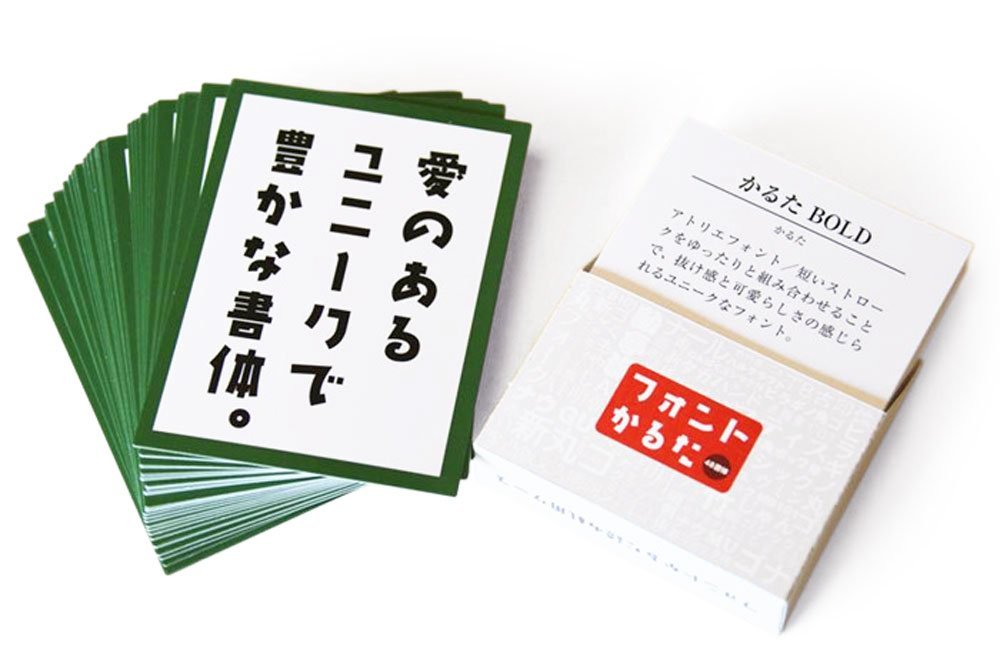
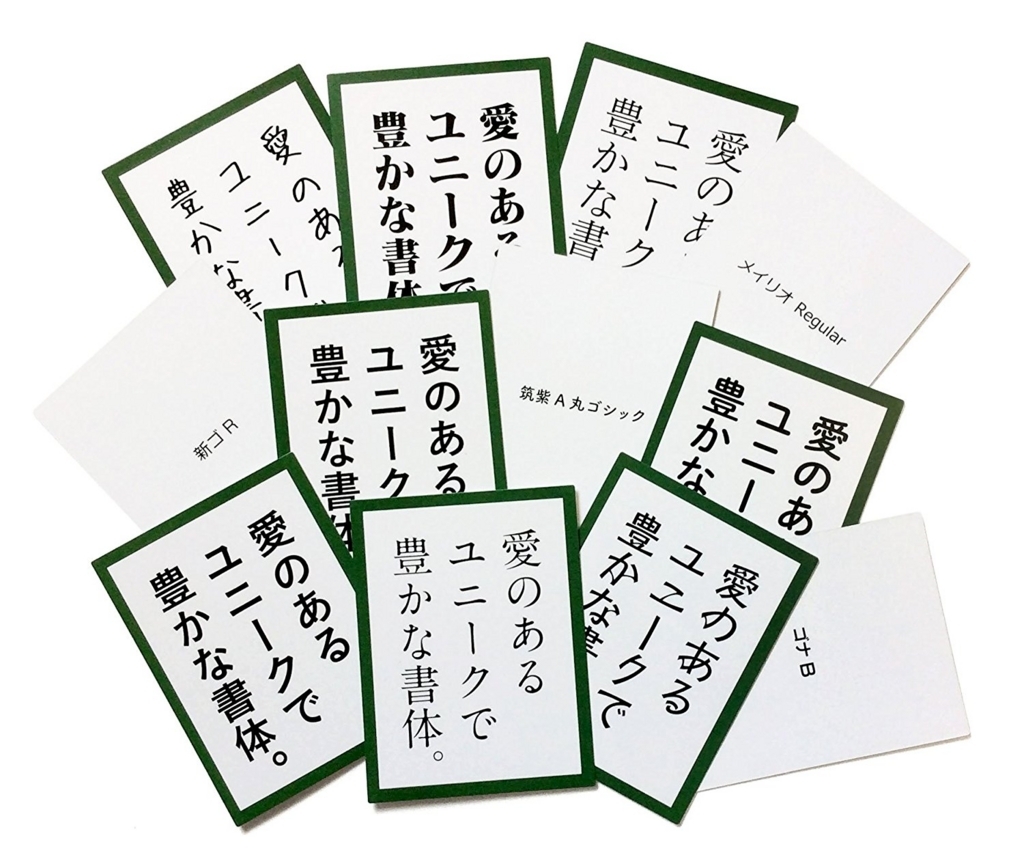
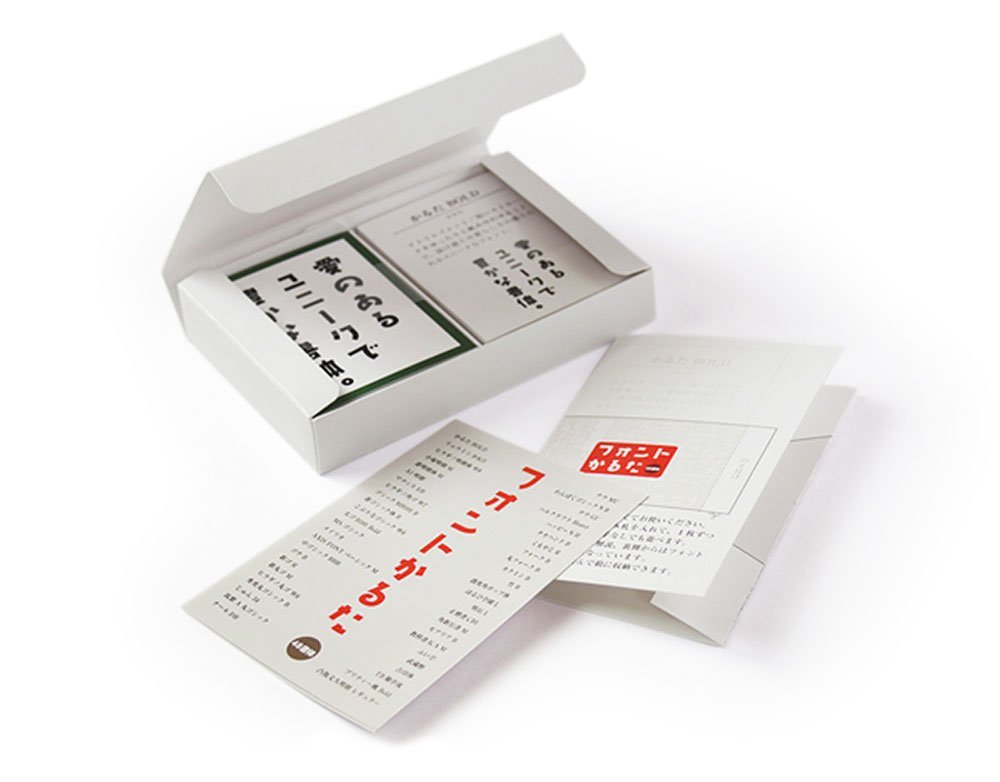
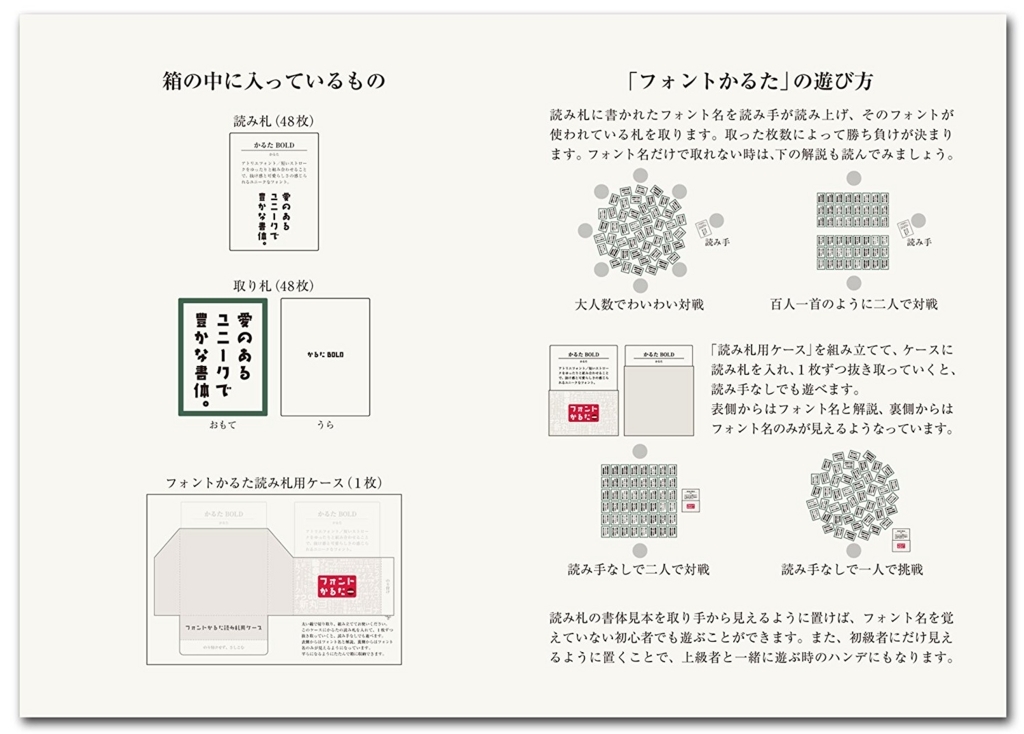
「フォントかるた」採用書体
かるた BOLD
リュウミン B-KO
ヒラギノ明朝体 W8
小塚明朝 M
游明朝体 M
A1 明朝
マティス EB
ヒラギノ角ゴ W7
ゴシックMB101 B
游ゴシック体 B
こぶりなゴシック W6
太ゴB101 Bold
MS ゴシック
メイリオ
AXIS FONT ベーシック M
中ゴシックBBB
ゴナB
新ゴ R
新丸ゴ M
ヒラギノ丸ゴ W6
秀英丸ゴシック B
じゅん 34
筑紫A 丸ゴシック Bold
ナールDB
ナウ MU
わんぱくゴシックN B
ナウ GU
ハルクラフト Heavy
ハッピーN H
タカハンド B
くもやじ R
フォーク B
丸フォーク B
カクミン B
竹 B
創英角ポップ体
はるひ学園 L
明石 L
正楷書CB1
角新行書 M
モアリア B
教科書ICA M
ふい字
武蔵野
TB 古印体
勘亭流
プリティー桃 Bold
凸版文久明朝 レギュラー
計48書体が採用されている。
もちろんフォントデータはついていない。
パッとみた感じではモリサワフォントが多い印象を受けた。
第1回FKS48総選挙!
「第1回FKS48総選挙!」と称したフォントかるた人気投票が実施された。
選挙後に「私、FKS48のA1明朝は結婚します!」といった爆弾発言が飛び出すのかどうか期待したいところ。
「フォントかるた拡張パック白」「フォントかるた拡張パック黒」
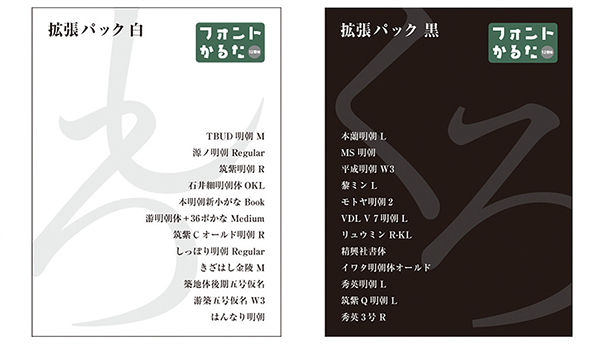
「カルタ名人もビンタ上手い説」もクロちゃんにより立証される中、フォントかるた制作チームは、従来の「フォントかるた」の拡張パックとして「フォントかるた拡張パック白」「フォントかるた拡張パック黒」を新たに制作したと11月1日に発表した。
それぞれの拡張パックは、「フォントかるた」に追加する形で遊ぶことができるようになっている。
拡張パック白・黒は、従来の「フォントかるた」から、更に深い書体の愉しみを見つけることができるようにとのコンセプトのもとで制作された。どの札の文字も一瞬、同じように見えてしまうが、よくよく見比べてみる事で、かなと漢字の大きさのバランス、フトコロの大きさ、起筆や終筆の形の違いなど、どの字形も同じものではなく、見比べることで書体デザインの系譜、日本語書体の美しさと奥深さに気付くことができる。
フォントかるたとは…
取り札はテキスト字体は全く同じだが、それぞれ異なった書体が使用された読み上げられたフォント名の札を当てて取るとかるた。基本セットには48枚ずつの取り札と読み札が含まれている。
自分はイベント会場で定価より安く売っていたので当時、一つ購入した。
フォントかるたで遊ぶのも意外と鬼畜仕様
フォントかるたを購入したのは良いが、よくよく考えたら、フォント名を詠む人間に加え、対戦する相手が一人以上必要で、また、その人間達がある程度はフォントに詳しくなければならないという難題に気づき、現在、フォントかるたは観賞用オブジェと化している。
フォントかるたは、ぼっちには厳しく、パリピなフォント好きに向いているといえる。是非、フォント好きが集まる忘年会や新年会などで…遊んでほしい。
「今までのフォントかるたでは物足りない」というフォントに詳しいユーザーの声に応えるべく、比較的高難易度の仕様となっており、一瞬では同じように見え、注意深くエレメントなどを見比べないと正しい札を取れないようなフォントが集められた。
「フォントかるた拡張パック 白」の収録書体は、TBUD 明朝 M、源ノ明朝 Regular、 筑紫明朝 R、石井細明朝体OKL、本明朝新小がな Book、游明朝体+36ポかな Medium、筑紫C オールド明朝 R、しっぽり明朝 Regular、きざはし金陵 M、築地体後期五号仮名、游築五号仮名 W3、はんなり明朝となっており、「フォントかるた拡張パック 黒」には、本蘭明朝 L、MS 明朝、平成明朝 W3、黎ミン L、モトヤ明朝2、VDL V 7 明朝 L、リュウミン R-KL、精興社書体、イワタ明朝体オールド、秀英明朝 L、筑紫Q 明朝 L、秀英3号 Rが収録となった。
収録書体をみると、今回の拡張パックのテーマは明朝体という事になるだろう。
「源ノ明朝」や「筑紫Q 明朝 L」といった書体が早速追加させているなど、新書体への対応に素早さを感じる拡張パックになってる。
また次回はテーマをゴシック体にするなりなんなり、今後、幾らでも拡張していける商品であり、売れ続ける限りは拡張パック商売で儲けていけるなぁと改めて感心させられた。
次回の商品名は「フォントかるた拡張パック金」「フォントかるた拡張パック銀」といった感じになるのだろうか。
2020年東京五輪で需要が高まる誰にでも読みやすいUDフォントを集めた「フォントかるた拡張パック金メダル」もお願いしたい。いつか「フォントかるた拡張パック ウルトラサン」「フォントかるた拡張パック ウルトラムーン」も登場してほしい。
▼フォントかるた拡張パック 白
収録書体
TBUD 明朝 M
源ノ明朝 Regular
筑紫明朝 R
石井細明朝体OKL
本明朝新小がな Book
游明朝体+36ポかな Medium
筑紫C オールド明朝 R
しっぽり明朝 Regular
きざはし金陵 M
築地体後期五号仮名
游築五号仮名 W3
はんなり明朝
▼フォントかるた拡張パック 黒
収録書体
本蘭明朝 L
MS 明朝
平成明朝 W3
黎ミン L
モトヤ明朝2
VDL V 7 明朝 L
リュウミン R-KL
精興社書体
イワタ明朝体オールド
秀英明朝 L
筑紫Q 明朝 L
秀英3号 R
制作:フォントかるた制作チーム